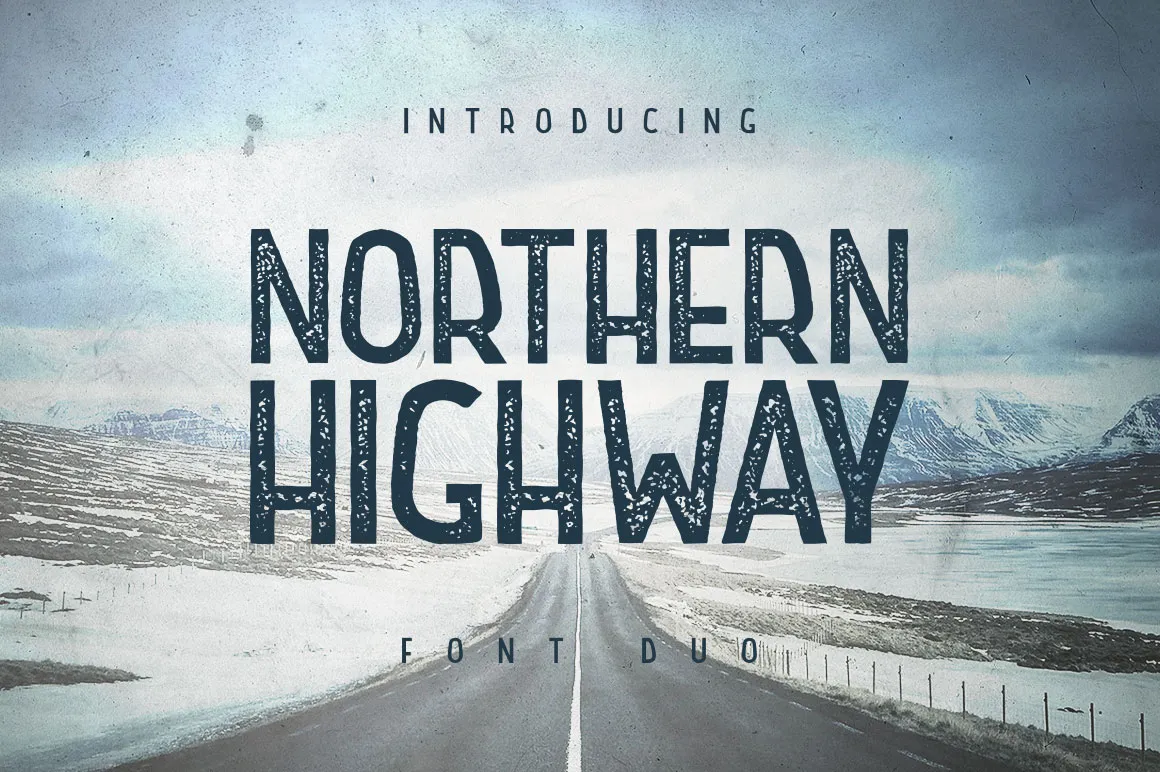
Northern Highway – Font Duo – Download Grátis
Northern Highway é uma nova fonte retro-vintage lançada pela designer seveniwe que combina dois estilos únicos: clean e rough, ambos com texturas levemente sujas. Este duo de fontes perfeito para design de logotipo, mantém um espírito vintage ao destacar o uso do texto grande da Northern Highway no centro de seu design. Adicione alguns segundo textos ou elementos gráficos e seu objeto de marcação e logotipo estarão concluídos! O resultado é um design rústico e cheio de personalidade. Esta fonte ideal para quem deseja incorporar um estilo retro-vintage em seus designs, seja em impressões digitais ou físicas. Suas linhas simples mas contidas combinam perfeitamente com texturas suaves e desgastadas que dão ao design um toque único e vintage. Ideal para aqueles que querem uma paleta de opções para personalizar suas criações, seja para criar logotipos distintivos ou qualquer outro tipo de design gráfico.